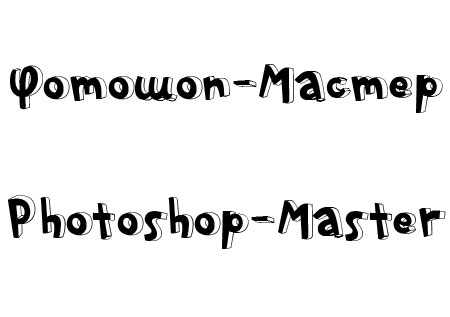
Дополнения Шрифты Татьяна Гапонова 7 августа 2009 Шрифт - PFPlayskoolPro-3D Интересный объёмный шрифт, с поддержкой русского языка. Скачать Шрифт - PFPlayskoolPro-3D
Классный шрифт...Но у меня почему он пишет простыми, а не как на картинке
Очень пригодится для оформления детских коллажей. Спасибо.